今回は、ふわふわ・キラキラ・ときめきいっぱいの「ゆめかわ」な世界観にぴったりの日本語フリーフォントをご紹介します。
パステルカラーや魔法、ユニコーン、おとぎ話のような幻想的なモチーフなど“夢みたいにかわいい”空気感を表現するには、文字にもやさしさや甘さ、ときには少しだけミステリアスなニュアンスが欠かせません。
今回は、ふんわりとした手書き風、メルヘンチックな装飾系、ガーリーでちょっぴりファンタジックなフォントを中心にまとめてみましたので、ぜひ“ゆめかわ”な世界にぴったりのフォントを見つけてくださいね。
「ゆめかわ」におすすめのフォントまとめ
以下のサンプル画像は本記事で紹介している一部ですが、ゆるふわで可愛らしいそんなフォントデザインをまとめてみました。
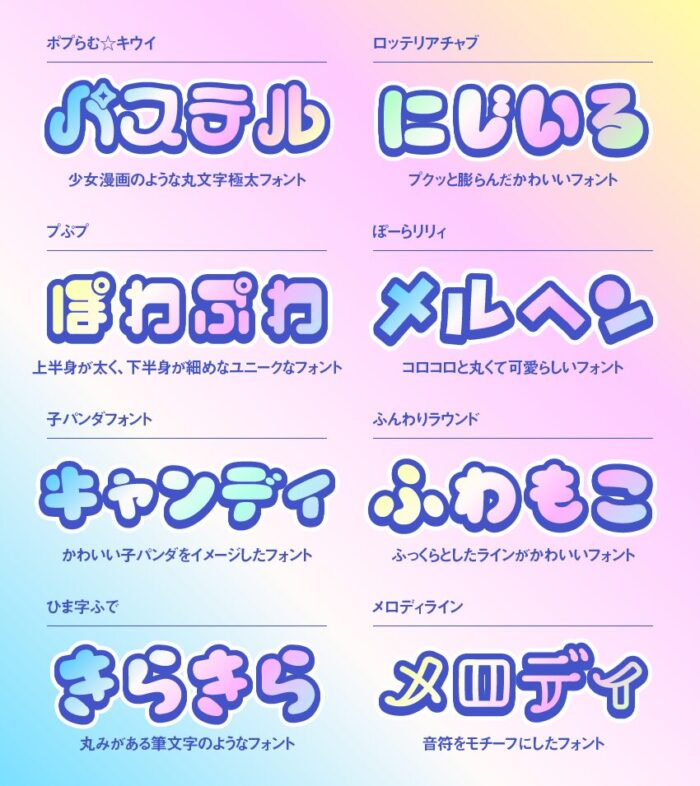
以下より、フォントのまとめになります。
ポプらむ☆キウイ
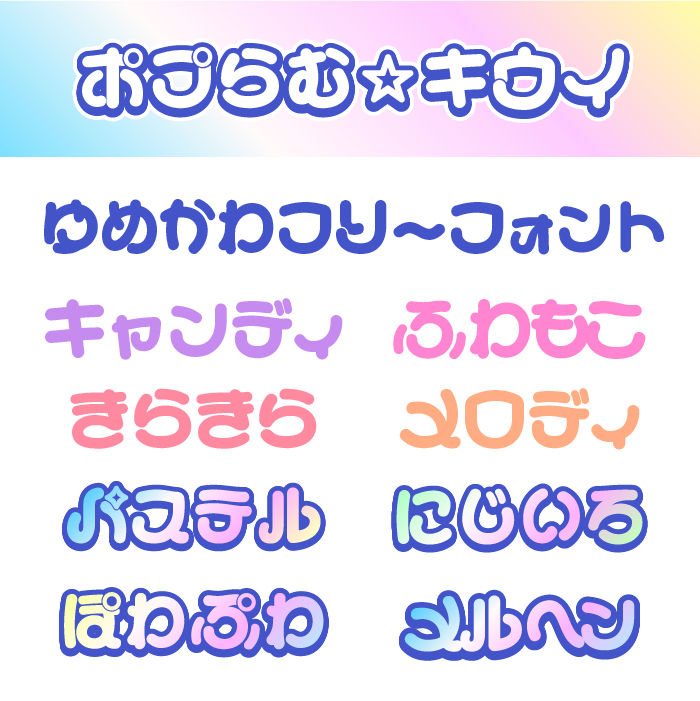
ポプらむ☆キウイフォントは、きらめきや星型の装飾が特徴的で、明るく前向きな気持ちを届けてくれるようなハッピーなフォントです。個性的なロゴやサブカル系デザインにも◎。
ロッテリアチャブ
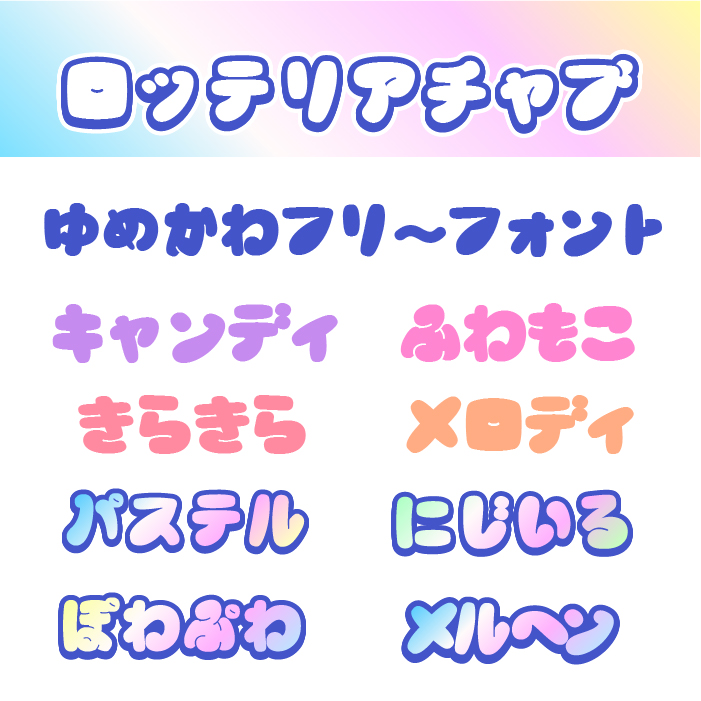
ロッテリアチャブフォントは、韓国ロッテリアが公式で提供しているフォントです。手描き風の味わいとレトロポップなシルエットが合わさった、元気でユニークで可愛らしい雰囲気のフォントです。
ぽーらリリィ
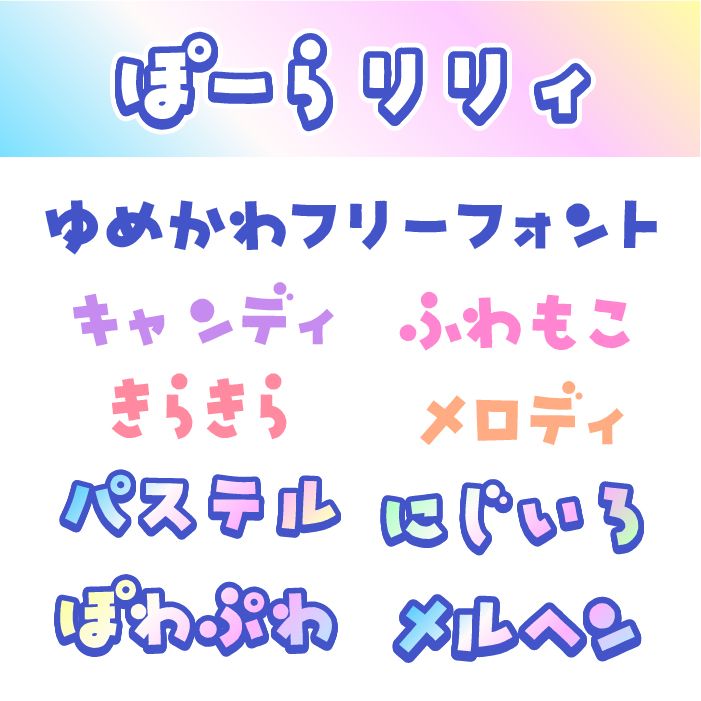
ぽーらリリィフォントは、文字の一部が丸やバブルのような装飾が入り、見ているだけでワクワクするような遊び心あふれるフォントです。とても可愛らしいので、ファンタジーやアイドル風デザインにぴったりです。
ふんわりラウンド
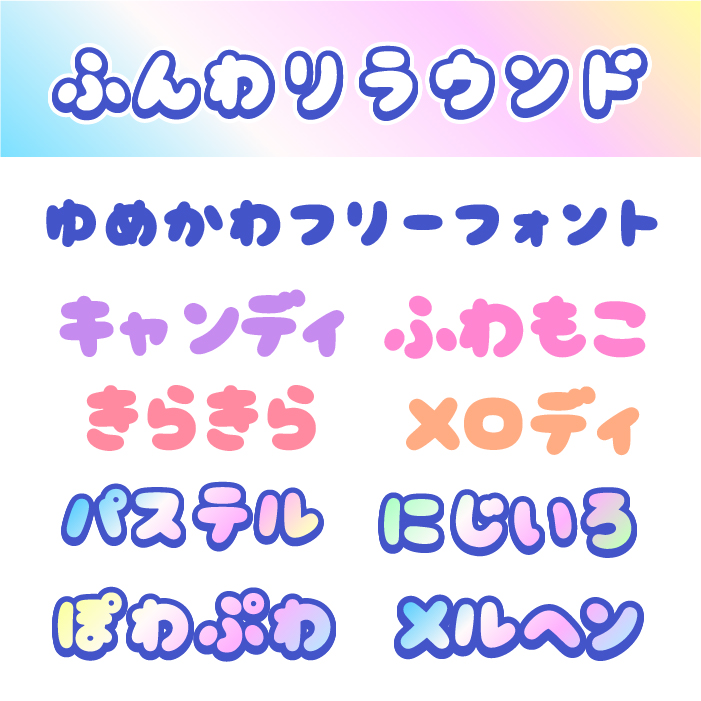
ふんわりラウンドフォントは、風船のようにふっくらとした曲線が特徴で、見るだけで癒されるようなゆめかわに満ちたフォントです。メルヘンやスイーツ系のデザインにぴったりです。
ひま字ふで
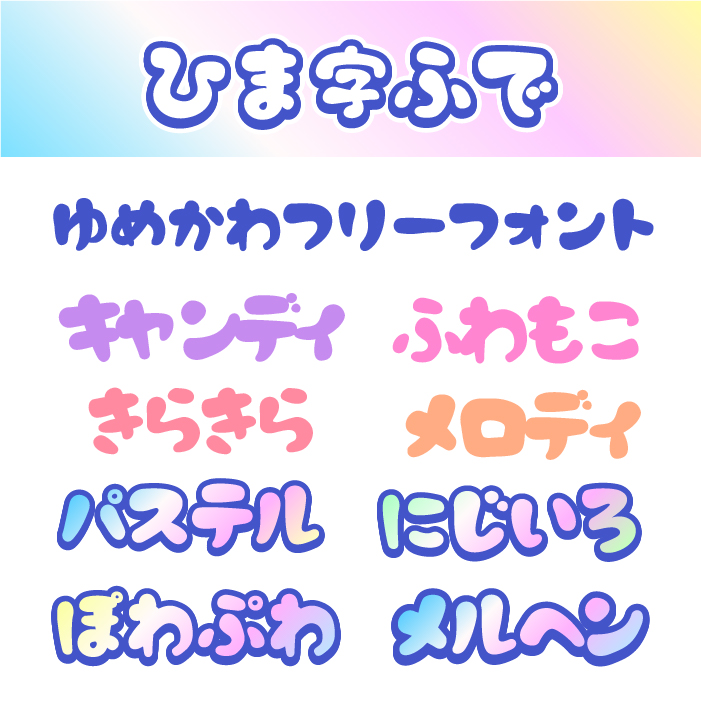
ひま字ふでフォントは、やわらかな筆跡のような自然な丸みとぬくもりがあり、読みやすさとかわいさを兼ね備えたフォントです。
Cherry Bomb
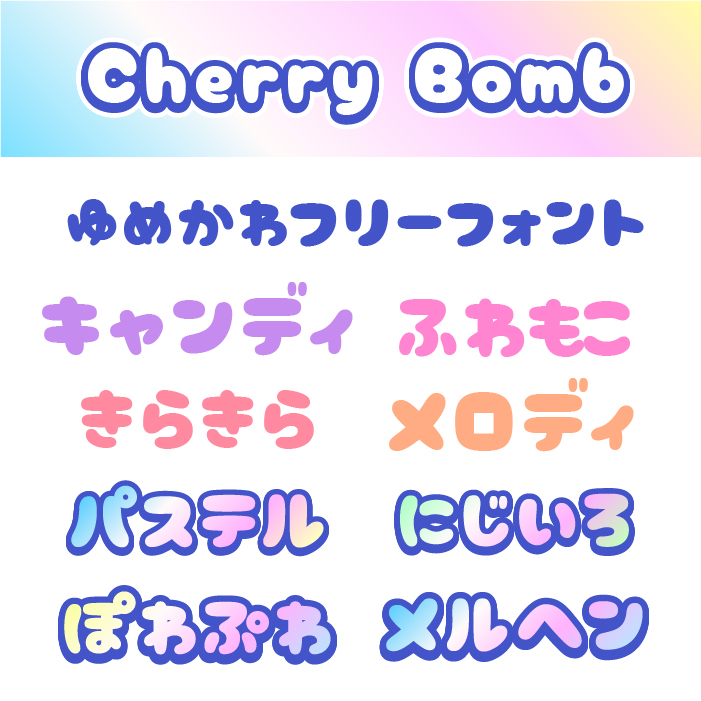
Cherry Bombフォントは、アメリカンコミックを思わせる元気な存在感と、キュートさを兼ね備えた「ゆめかわ」で賑やかなポップなフォントです。
ふわもこフォント
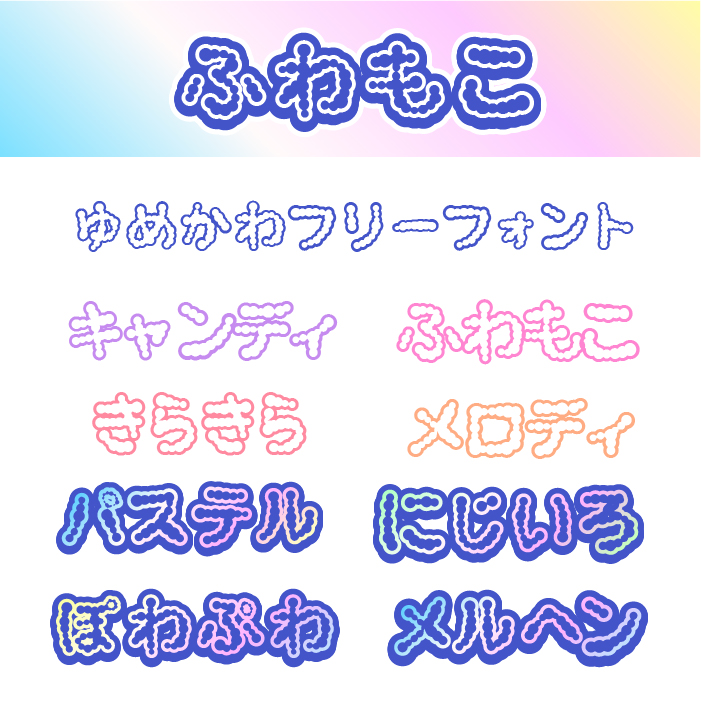
ふわもこフォントは、アウトラインで作られている綿菓子のようなふんわり感と手描きのようなやさしさを併せ持つ、柔らかくて甘い雰囲気のフォントです。ガーリーなデザインやSNSの投稿にもぴったりです。
子パンダフォント
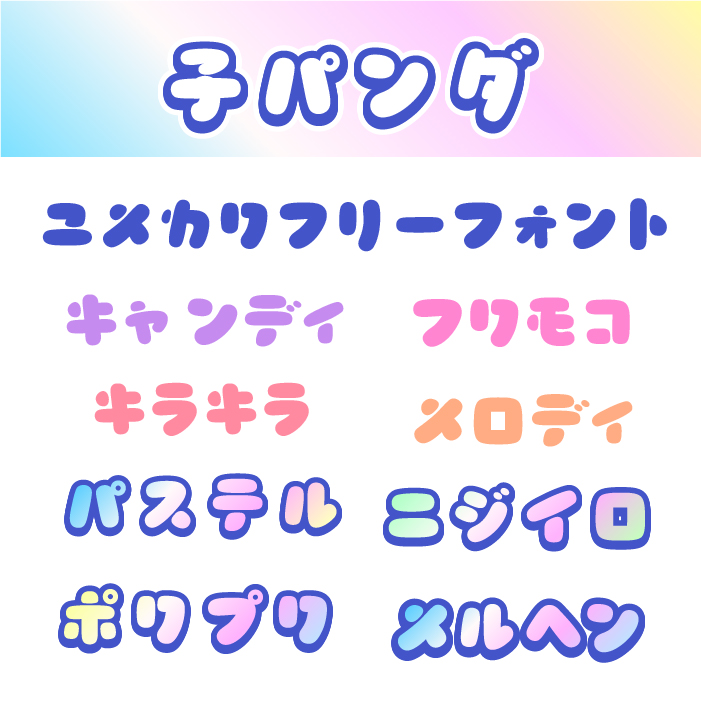
子パンダフォントは、パンダのぬいぐるみのような丸っこいフォルムと素朴な可愛さが魅力で、太めのシルエットがやさしくインパクトを与えるフォントです。
メロディラインフォント
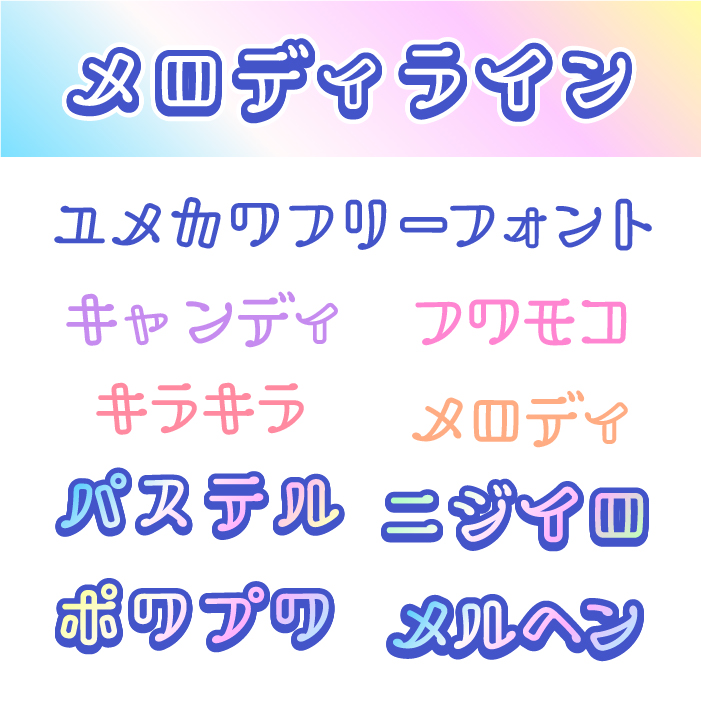
メロディラインフォントは、音楽のように軽やかでリズミカルな印象を持ち、丸みのあるアウトラインが特徴のポップでかわいいフォントです。パステル系のデザインや夢かわ系のロゴにぴったりです。
プぷプ
ぷプぷフォントは、駄菓子屋さんのようなちょっぴりレトロで懐かしい雰囲気を持ち、ポップで親しみやすい印象のフォントです。